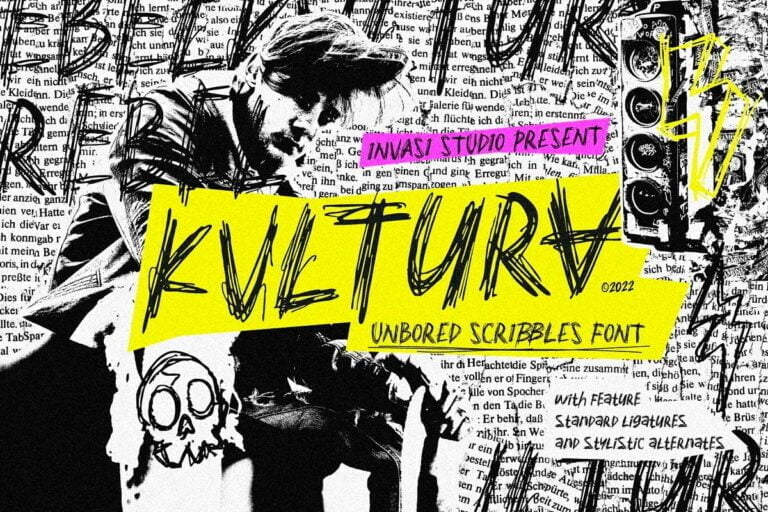
Bạn muốn thêm sự thô sơ vào thiết kế của mình. Phông chữ Kvltura có kiểu viết nguệch ngoạc không nhàm chán, giúp thiết kế của bạn nổi bật hơn. Kvltura là một phông chữ viết tay toàn chữ hoa. Bạn cũng có thể kết hợp bất kỳ ký tự nào với chữ ghép Kvltura và các ký tự thay thế để tạo ra một sự kết hợp đáng kinh ngạc!
Phông chữ này hoàn hảo cho dự án hiển thị của bạn dành cho tiêu đề, trích dẫn, thiết kế biên tập, in áp phích, v.v.
Features:
- Total 250 Glyph
- Uppercase
- Numerals & Punctuation
- Alternates & Ligature
- Multilanguage Supports 60+ Latin-based languages
Kvltura – Unbored Scribbles Font Preview